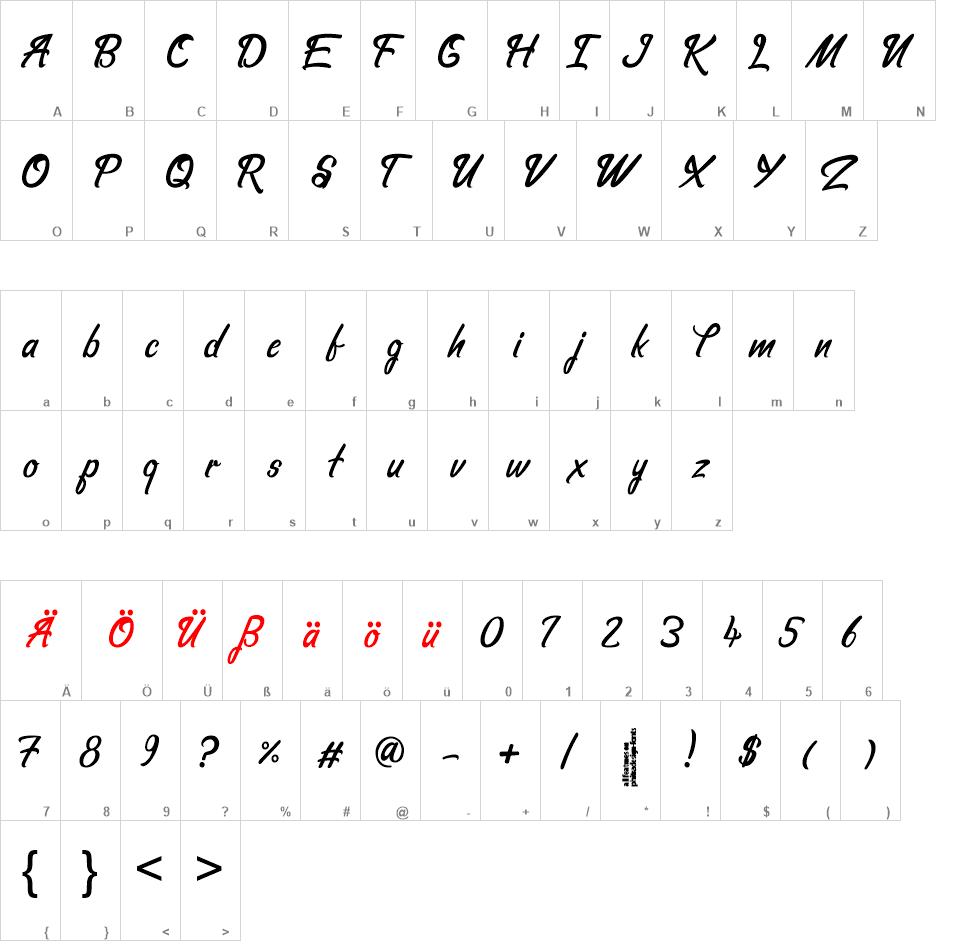
Hello Love
Hello Love font
Hello Love
Hallo Liebe ist eine einzigartige Pinselschrift mit Sprachunterstützung und 555 Glyphen. Es hat ein sehr modernes Aussehen und ist perfekt für jede Art von Logo, Präsentation oder Überschrift. Sie können die alternativen Buchstaben auch versuchen, etwas persönliche Note hinzuzufügen!